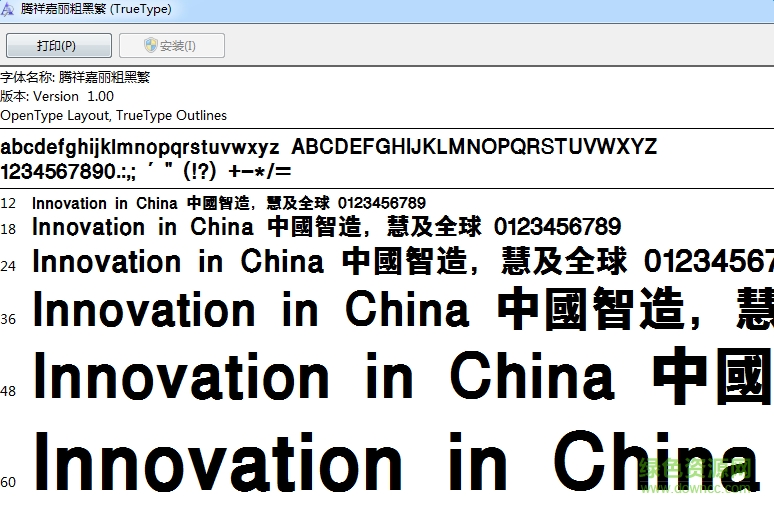
騰祥嘉麗粗黑繁體
騰祥嘉麗粗黑繁字體是一款應(yīng)用于設(shè)計方面的個性字體,改字體可用于藝術(shù)設(shè)計、包裝印刷、簽名設(shè)計、圖形設(shè)計等領(lǐng)域,有喜歡的朋友可免費(fèi)下載收藏。
騰祥嘉麗粗黑繁字體是一款極具個性的字體,該字體形體非常方正,有喜歡的朋友可以來綠色資源網(wǎng)下載體驗!